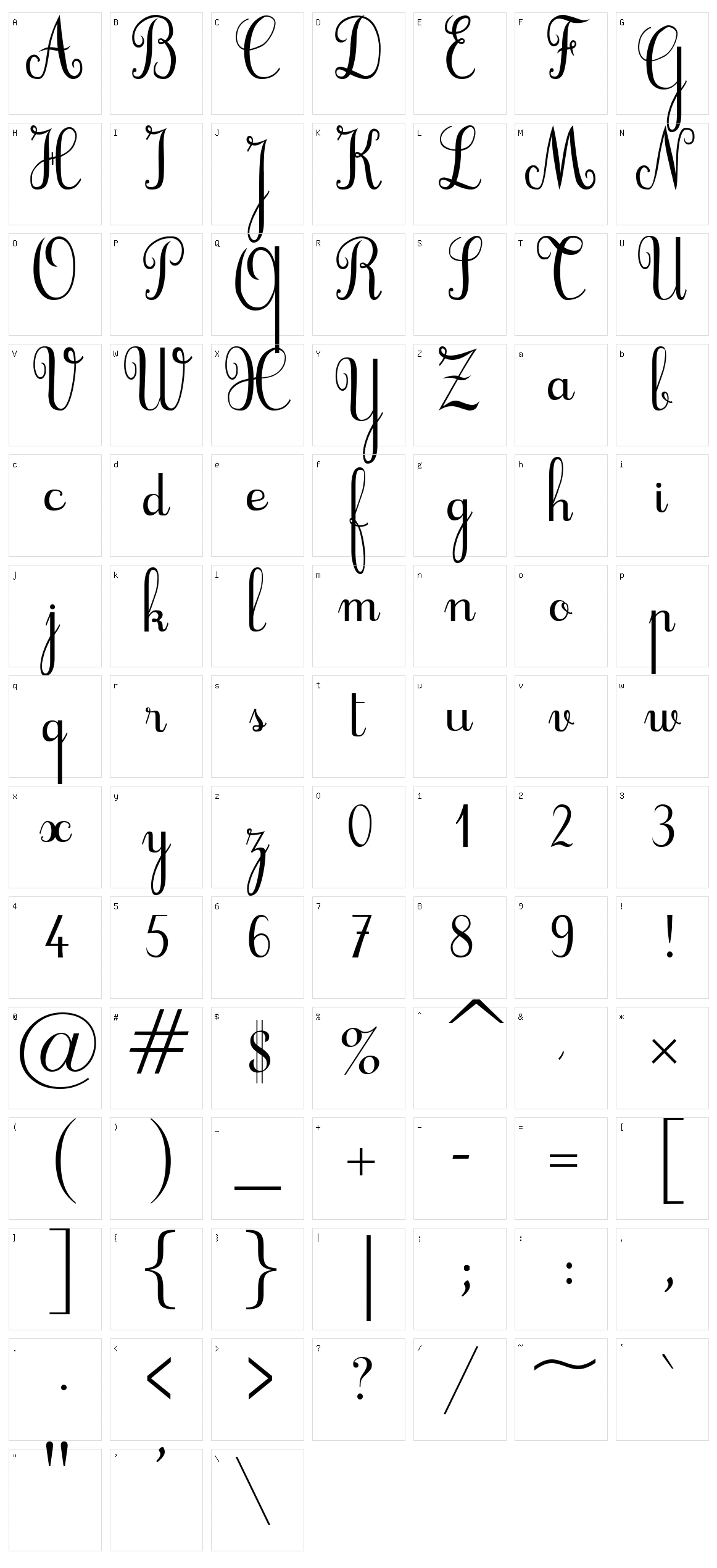
Cursif
Designed by: Christophe Beaumale
Police cursive de type manuscrite
Voici deux polices True Type qui permettent une écriture de type manuscrite ( un peut trop parfaite sans doute ).
Pour ces deux polices, la petite queue de premier caractère d'un mot se situe sur la touche & du clavier.
Ces deux polices ont été élaborées par BEAUMALE Christophe, enseignant débutant ( 1ère année en CP ).